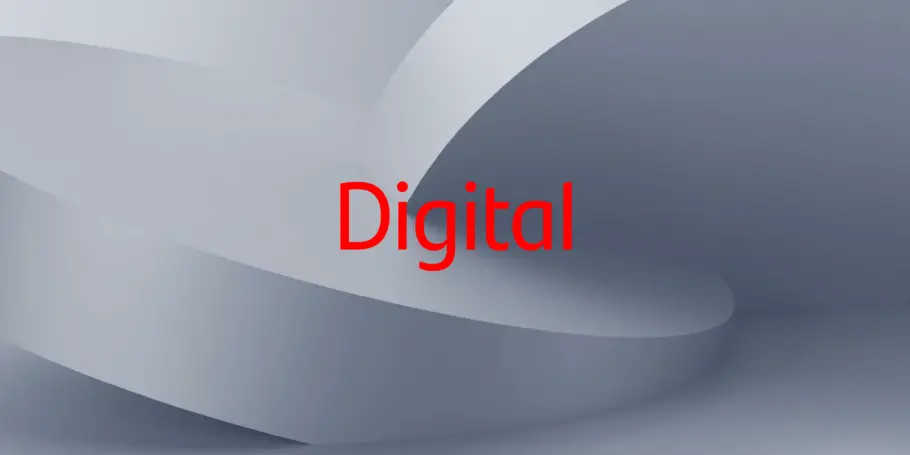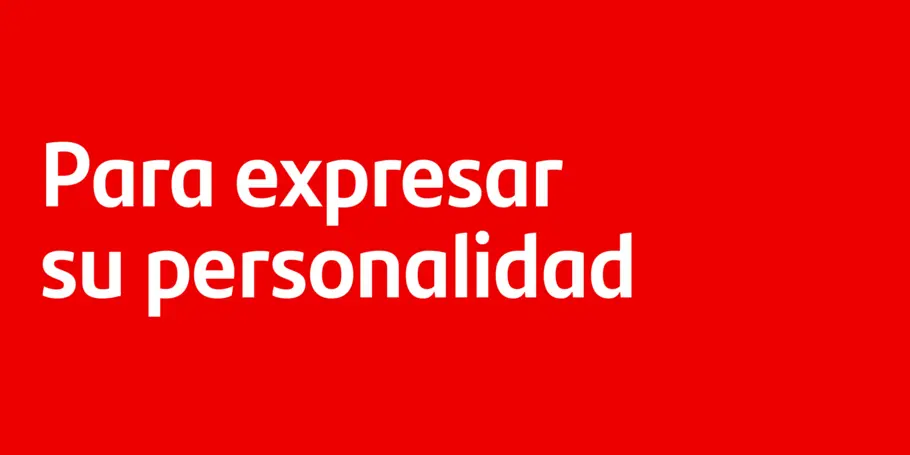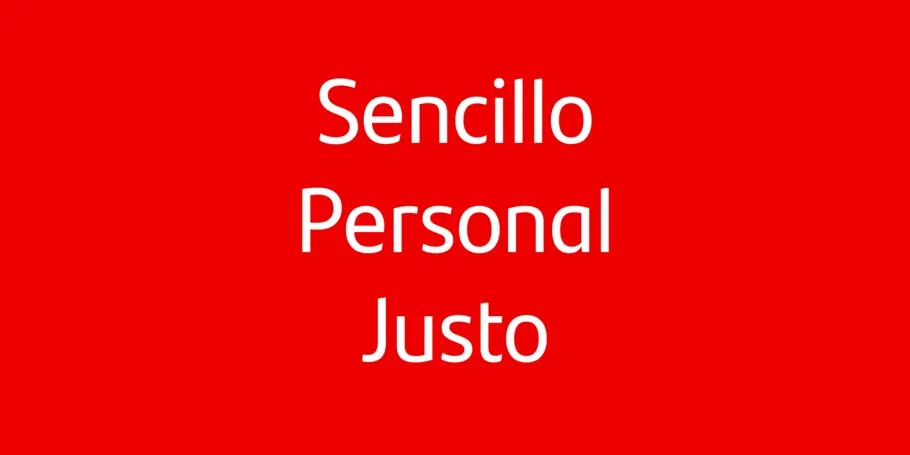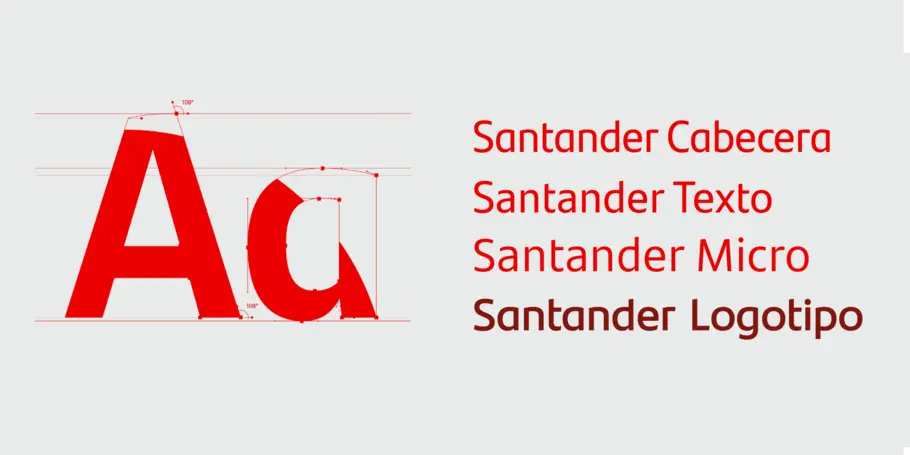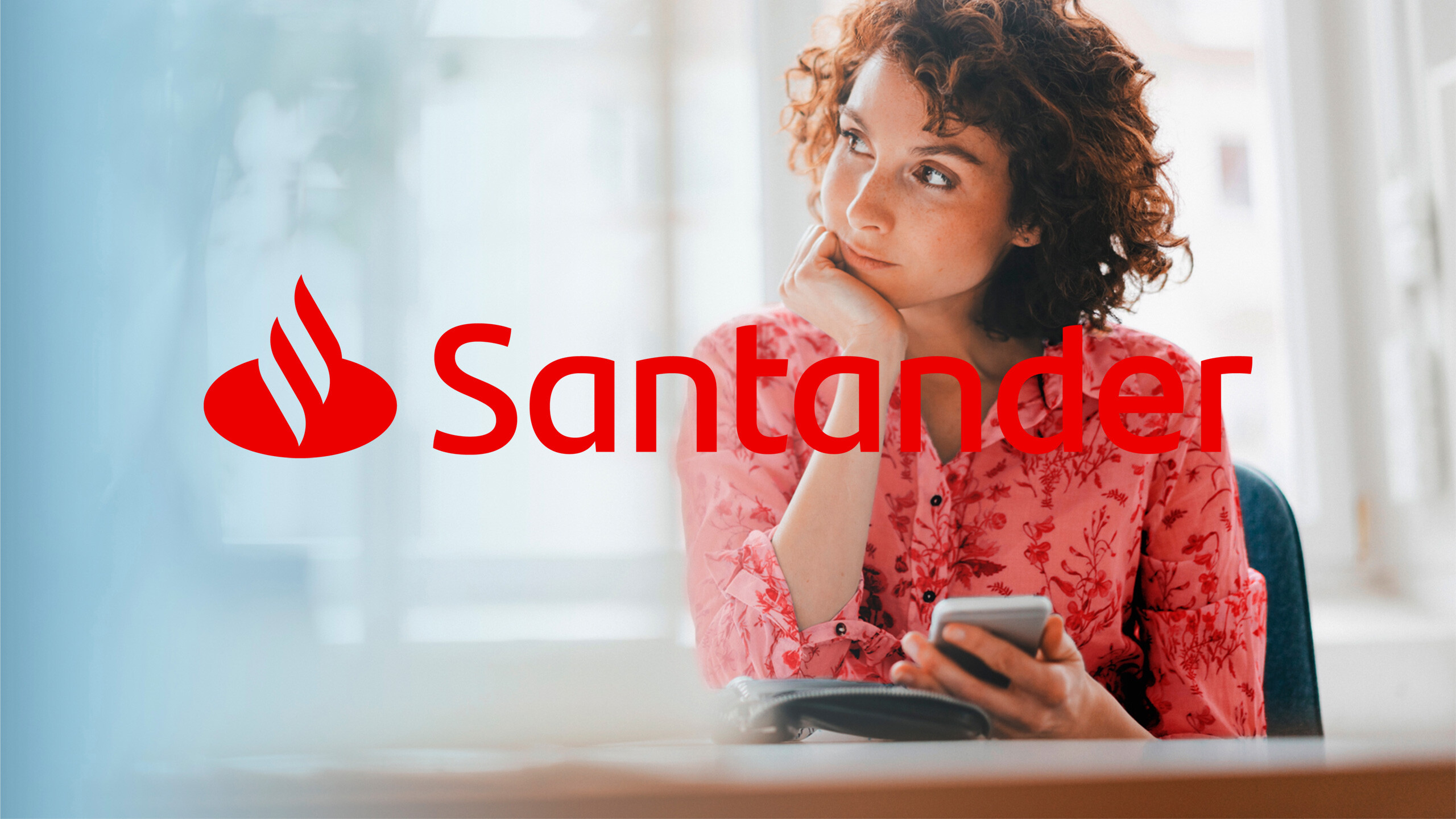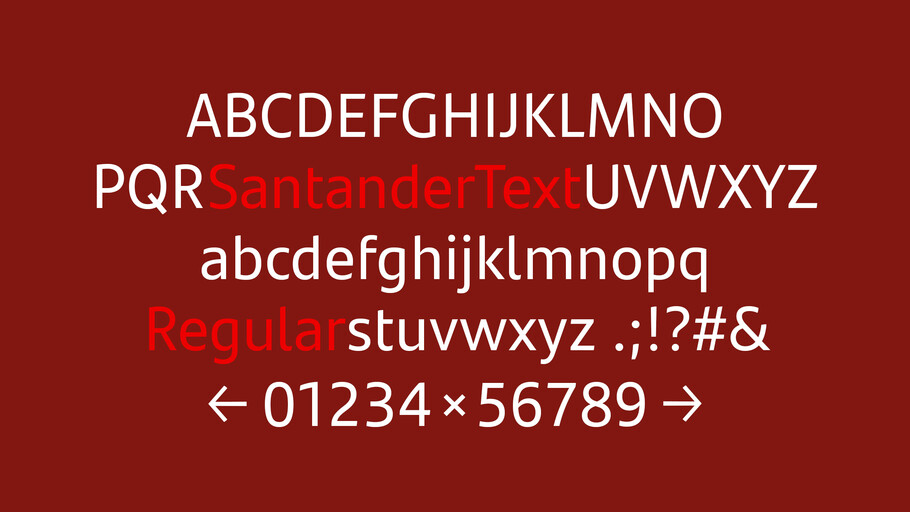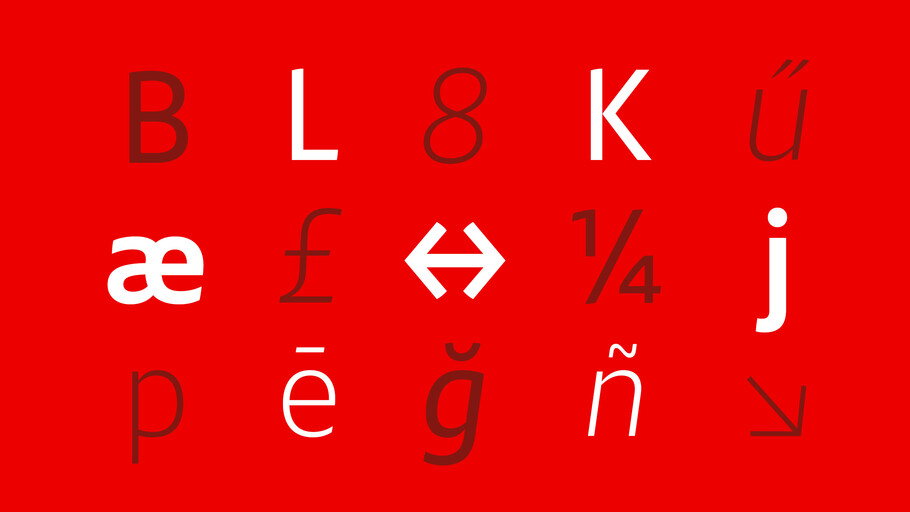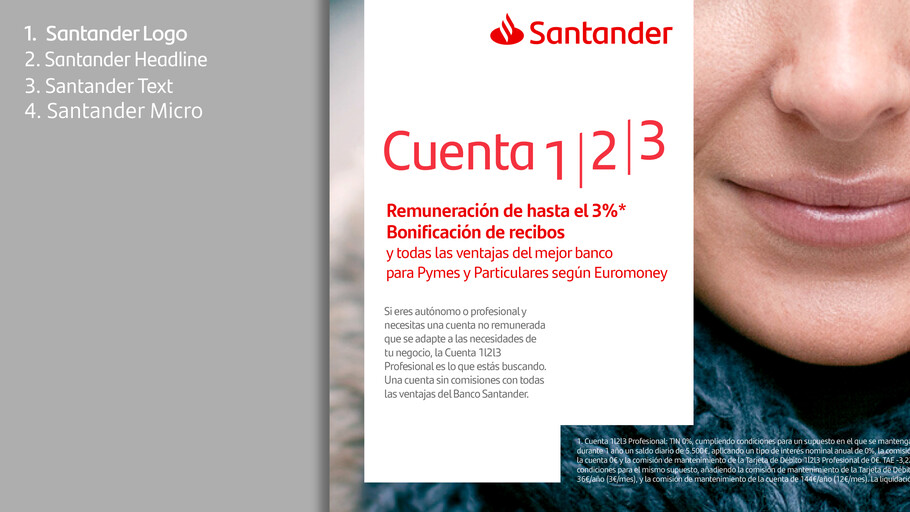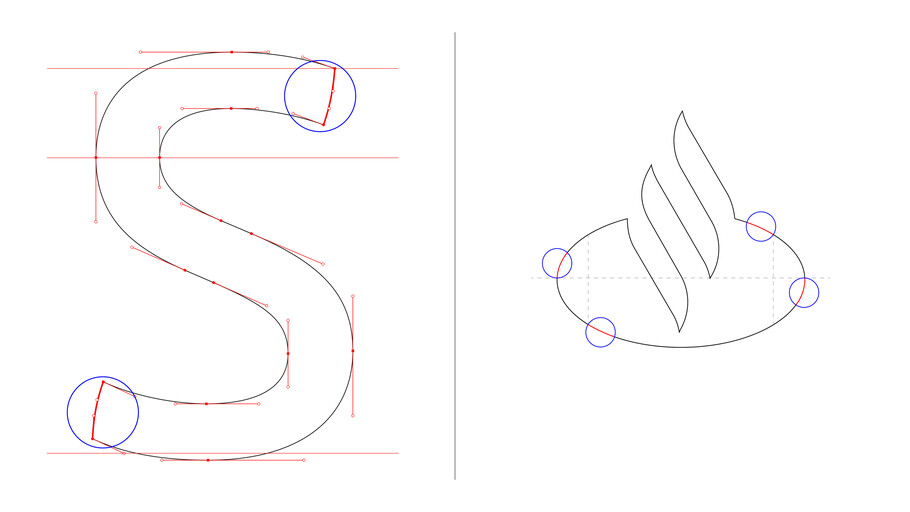
Santander.
Cabecera - Texto - Micro - Logotipo
Se muestra la palabra «digital» en la fuente de Santander
Sencillo - Personal - Justo
Cita que indica «para expresar su personalidad»
Cabecera - Texto - Micro - Logotipo